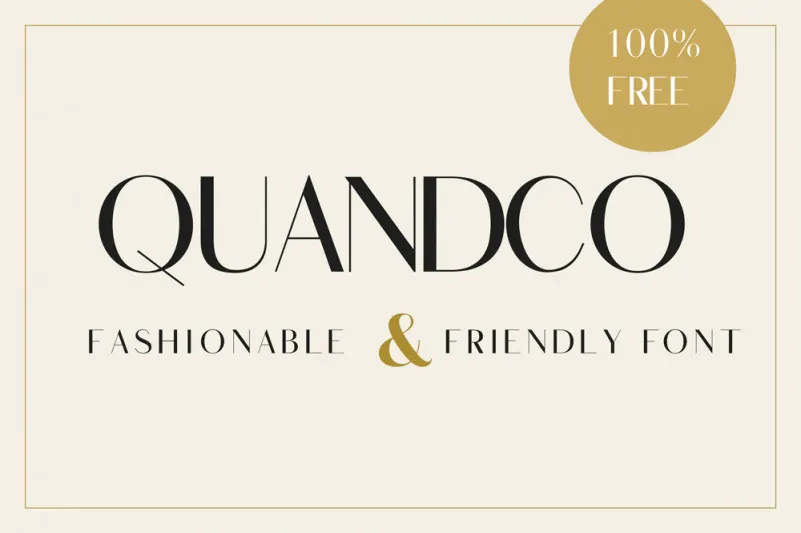
Quandco Sans Serif Font – Download Grátis
A fonte Quandco Sans Serif é uma tipografia sans-serif minimalista com potencial para se tornar a perfeita escolha para uso em logotipos, headlines e materiais de branding sem limite. Uma única olhada é suficiente para notar o estilo único deste tipo que fará com que ele seja ideal para tamanhos menores, especialmente para as cabeças pequenas e logotipos. Adicionar espaçamento extra entre os caracteres torna essa fonte perfeita para headlines e logotipos minimalistas, conforme mostrado nas gráficas de demonstração. Quandco é uma opção versátil que pode ser usada em múltiplas aplicações – web, impressão, identidade corporativa e design gráfico – sem comprometer o estilo ou a legibilidade. Com seu estilo elegante e limpo, Quandco é perfeito para projetos de marca que precisam de um look minimalista e sofisticado.